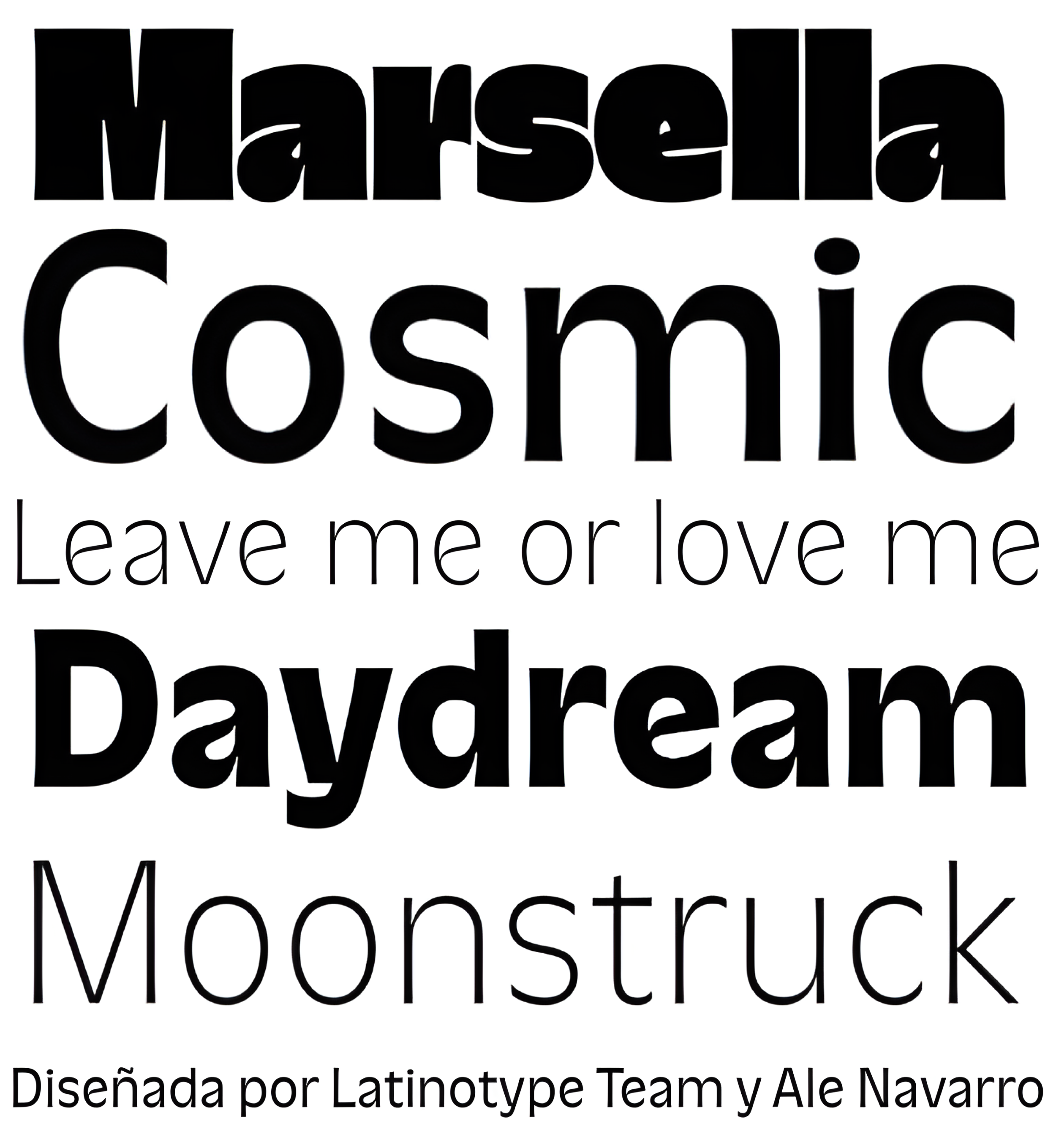
| Créditos | Ale Navarro, Latinotype Team |
| Descripción | Marsella es un tipo de letra que reinterpreta el espíritu de las fuentes humanistas francesas de los años sesenta con un toque moderno y artesanal. Su generosa altura x, sus delicadas gracias y sus proporciones equilibradas crean una estética refinada y atemporal. Elaborada con precisión, ofrece gramajes que van del fino al negro, junto con una variante de póster que eleva los espacios con composiciones compactas y dinámicas. Presenta glifos alternativos que amplían su versatilidad, mejoran la fluidez visual y garantizan un diseño armonioso, ofrece un repertorio de 575 glifos que le invitan a «soñar a lo grande y diseñar al detalle». Con sede en Concepción y Santiago de Chile, los fundadores de Latinotype afirman: «Nuestro objetivo es diseñar nuevos tipos de letra remezclando diversas influencias relacionadas con nuestra identidad sudamericana con productos de alta calidad para la industria del diseño contemporáneo». Y el dúo ha estado haciendo precisamente eso desde la creación de su fundición en 2007. |
| Familia(s) | Marsella |
| Estilos | 10 |
| Set | Especializado |
| Estudio | Latinotype |